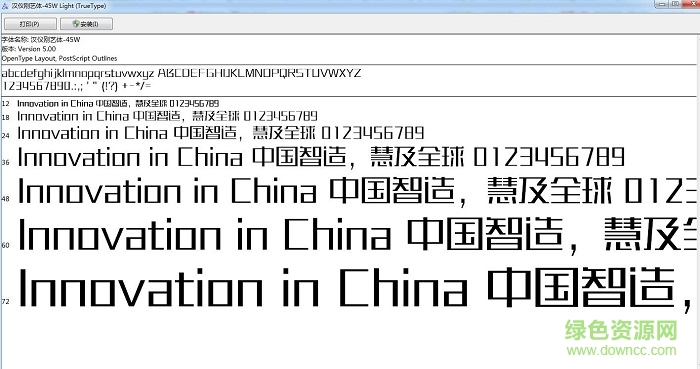
漢儀剛藝體 45簡(jiǎn) light
漢儀剛藝體-45w light字體是一款相對(duì)來說較細(xì)的漢儀字體,結(jié)構(gòu)嚴(yán)謹(jǐn),清晰易讀,可以廣泛應(yīng)用于廣告、標(biāo)題、名片、平面設(shè)計(jì)等領(lǐng)域,小伙伴們快來綠色資源網(wǎng)下載吧!
漢儀剛藝體 45簡(jiǎn) light